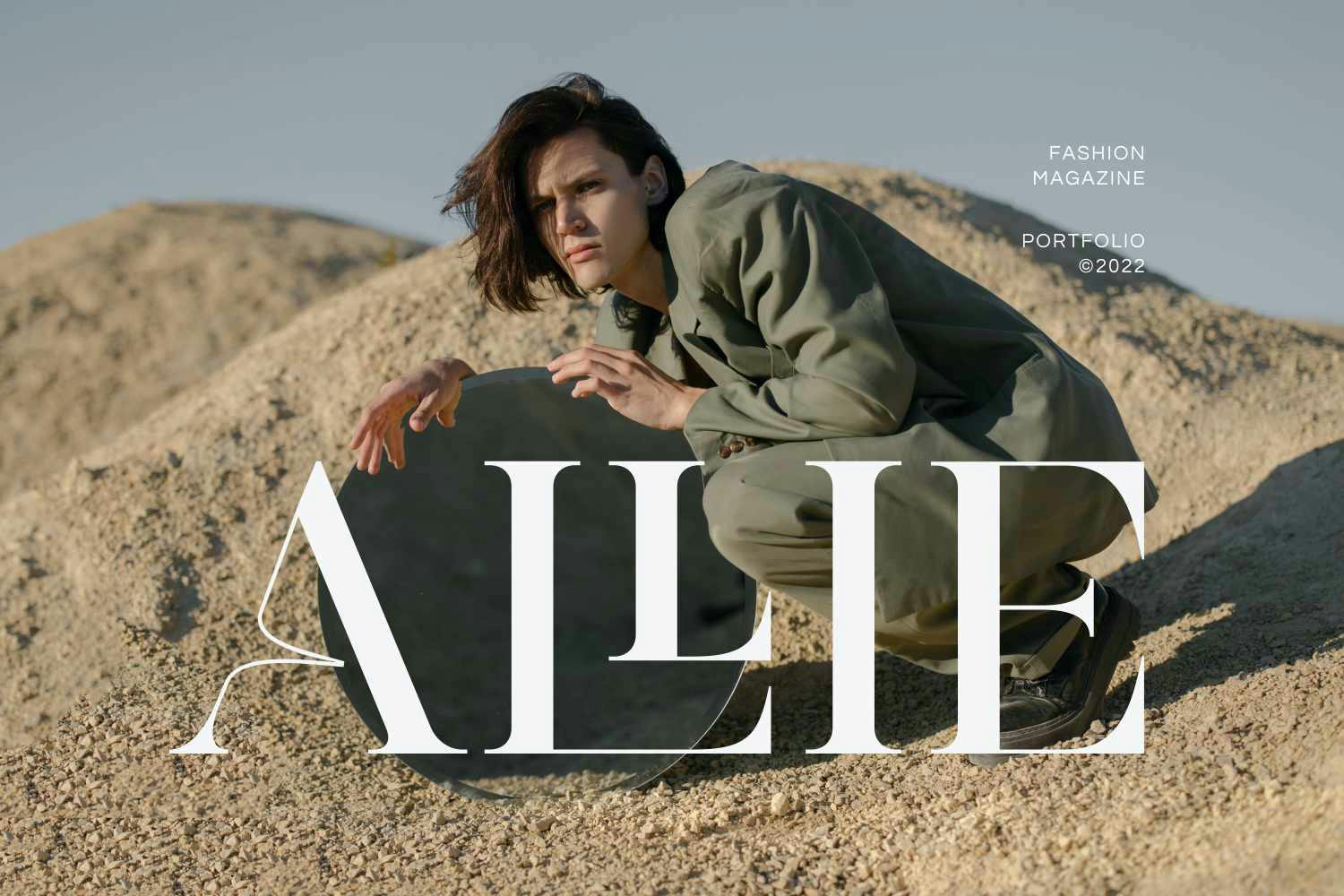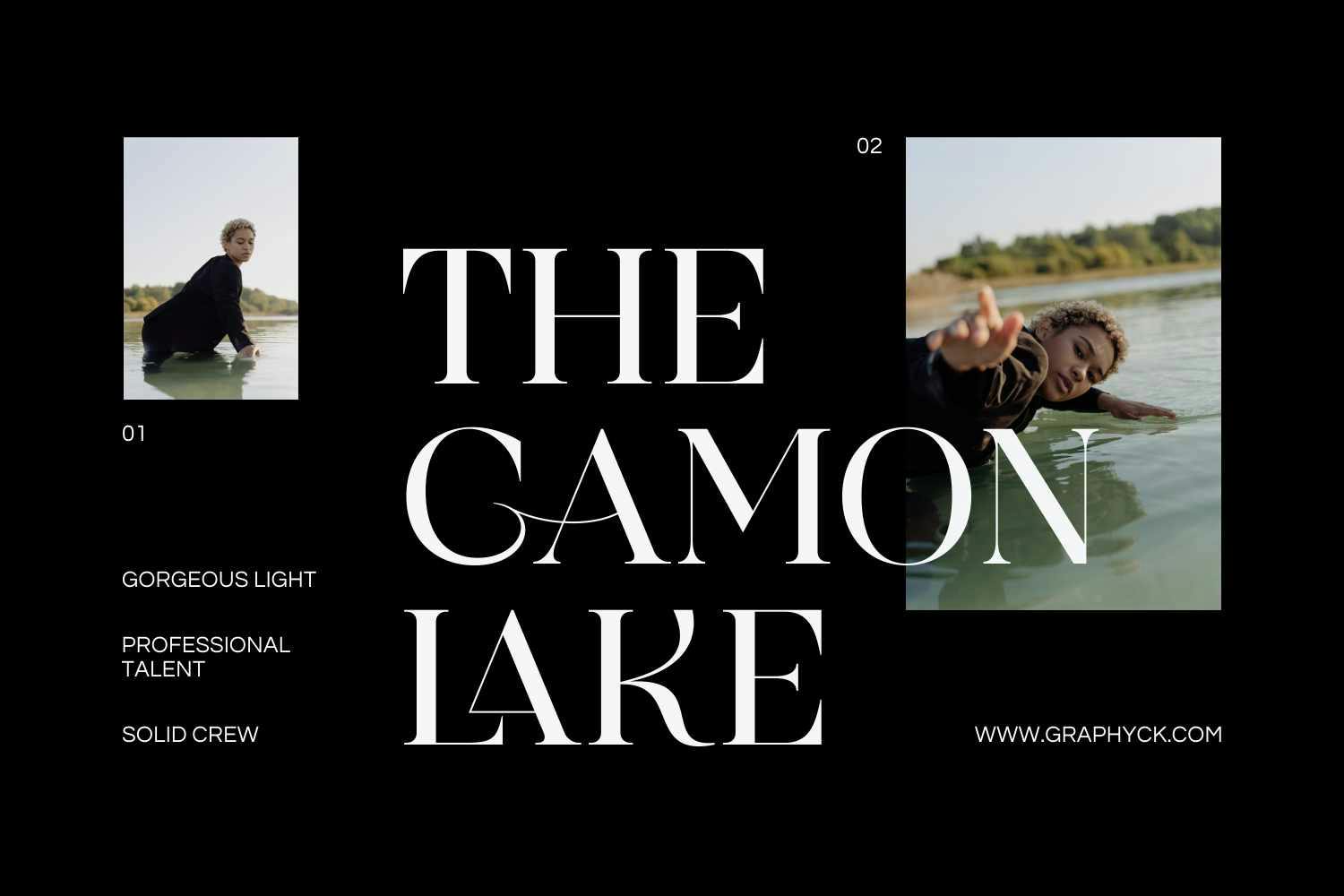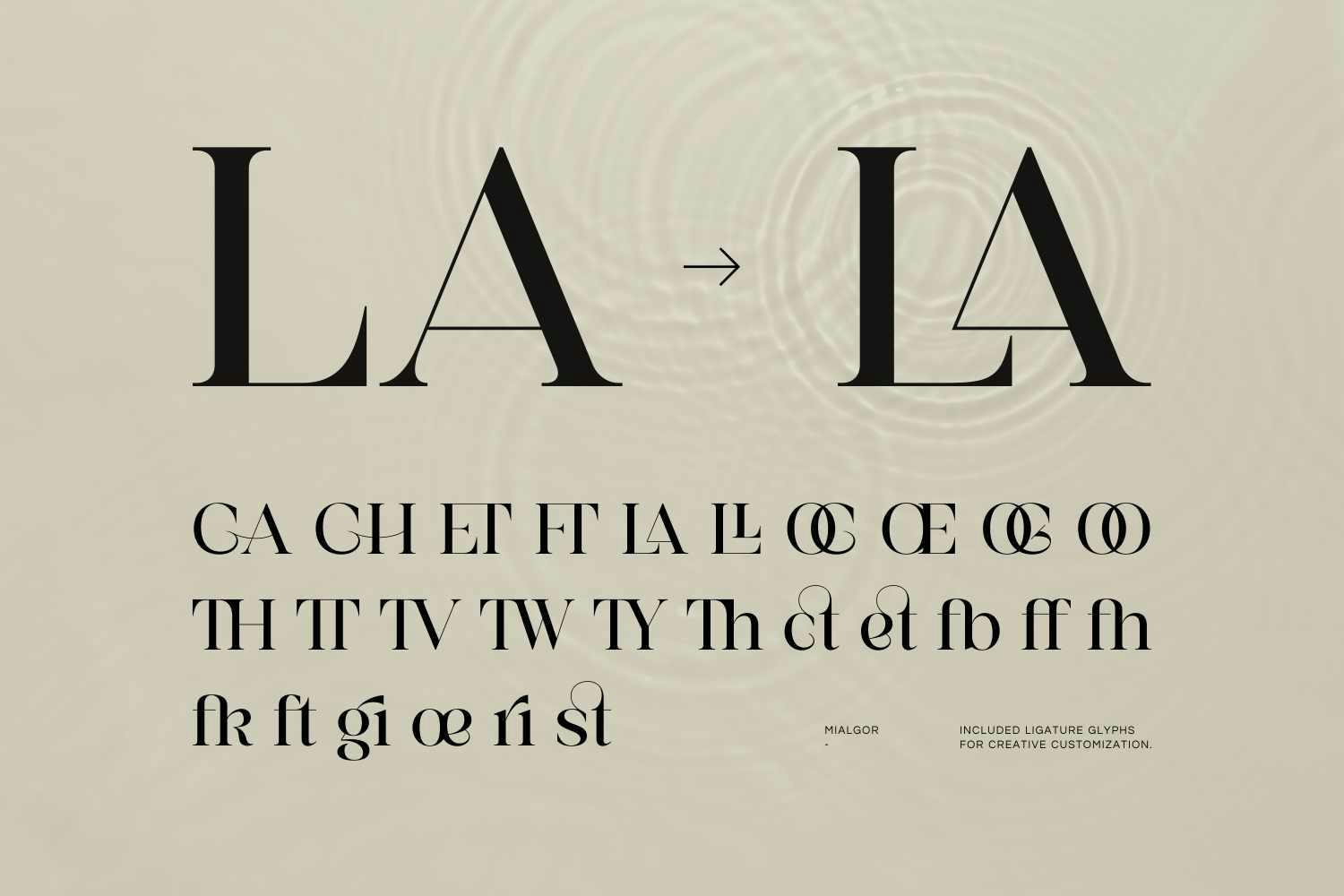
Mialgor یک فونت لوکس و کلاسیک است که با ظرافت بصری، منحنیهای نرم و لیگاتورهای زیبا، کار شما را جذاب و واقعی جلوه میدهد.
این فونت بسیار کاربردی است و در اندازههای بزرگ و کوچک به خوبی عمل میکند. فونت Mialgor برای پروژههای مختلفی مانند دعوتنامهها، لوگو، برندینگ، مجله، عکاسی، کارت، بستهبندی محصولات، ماگ، نقل قول، پوستر، برچسب، امضا و غیره مناسب است.